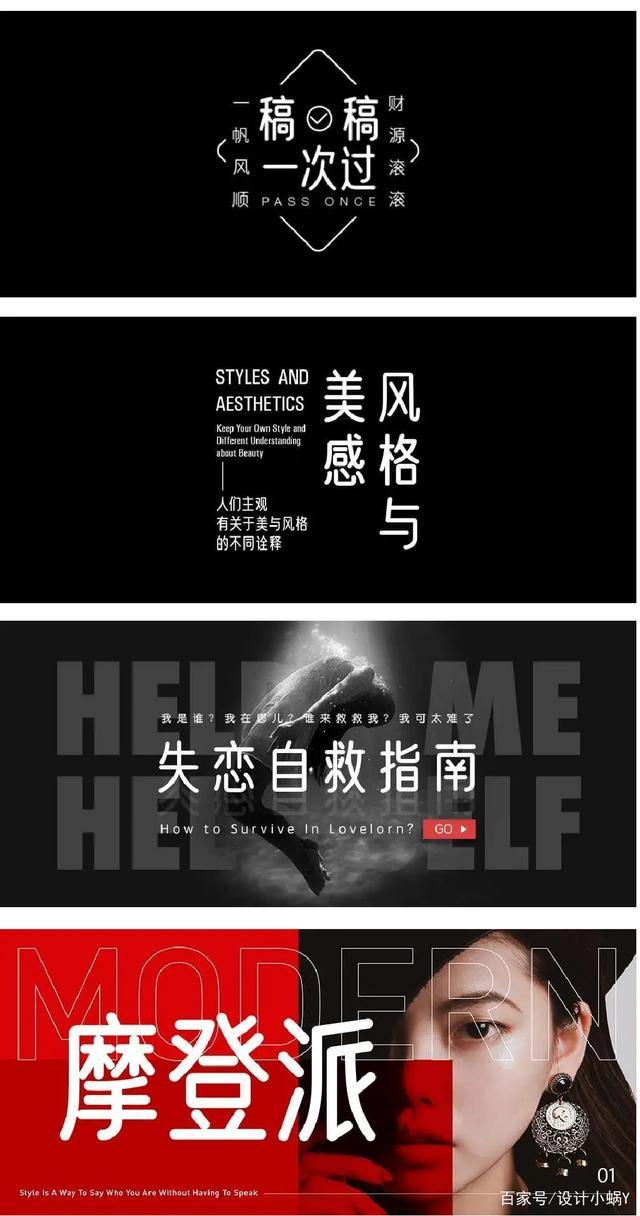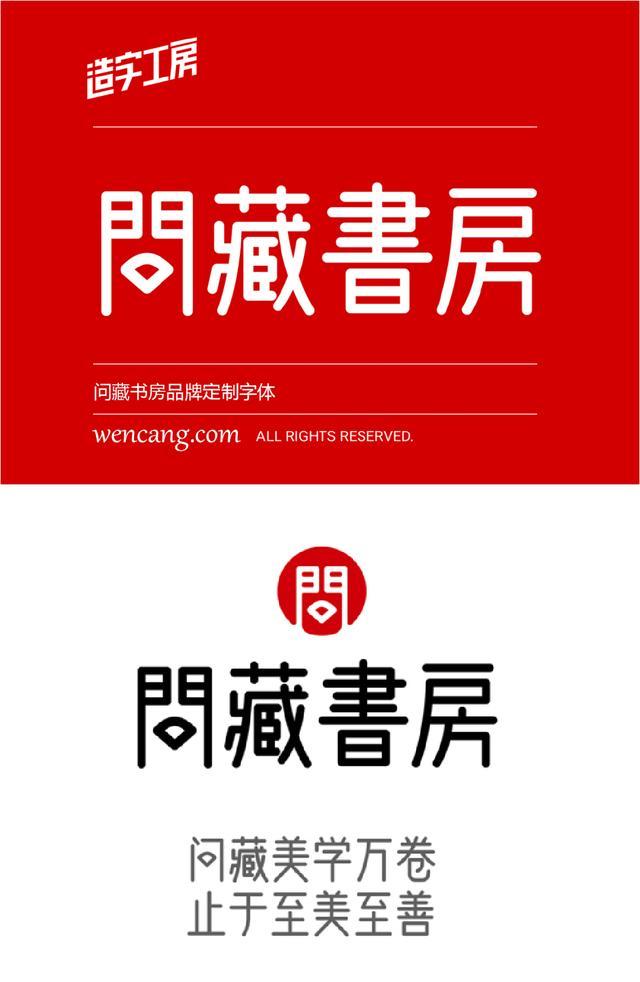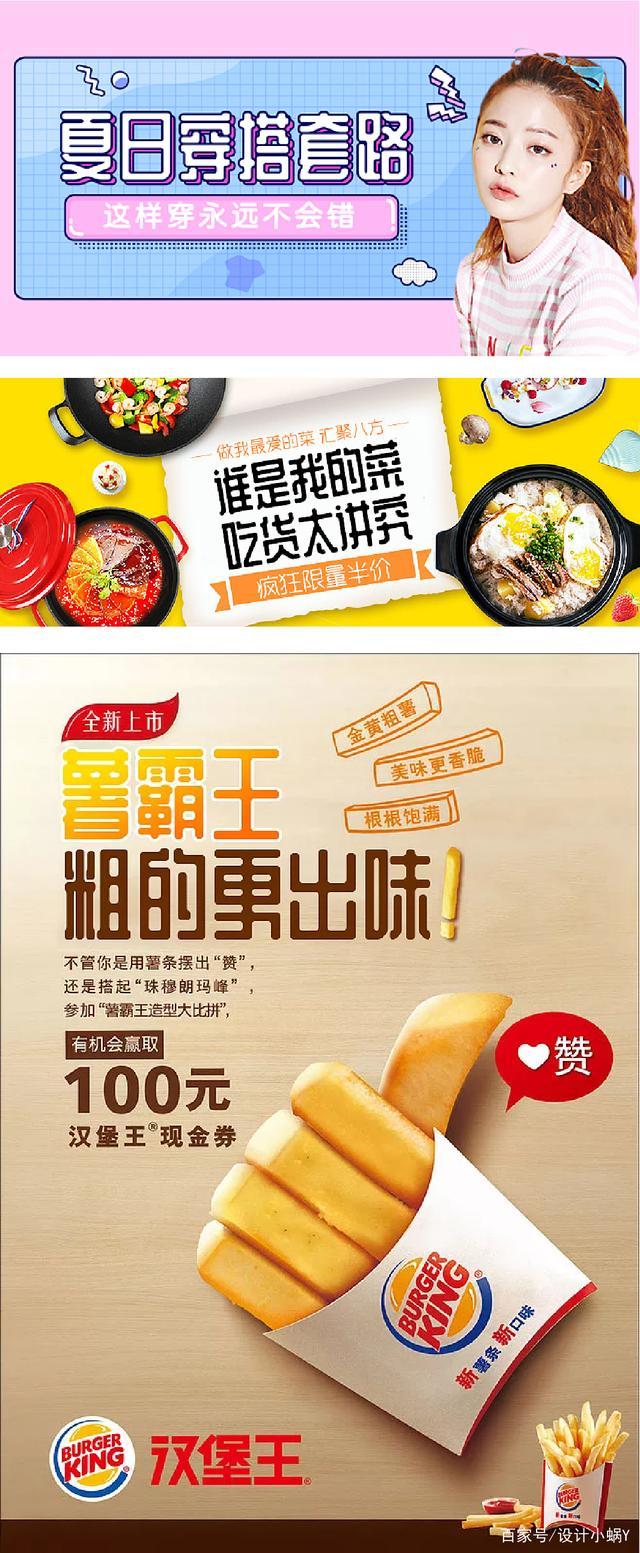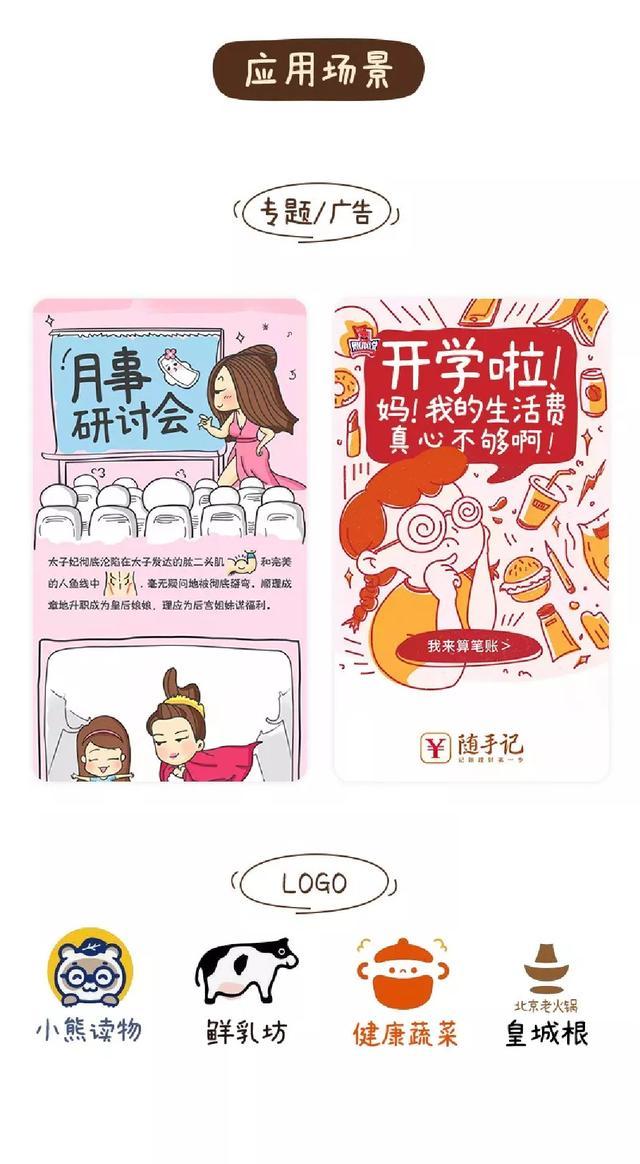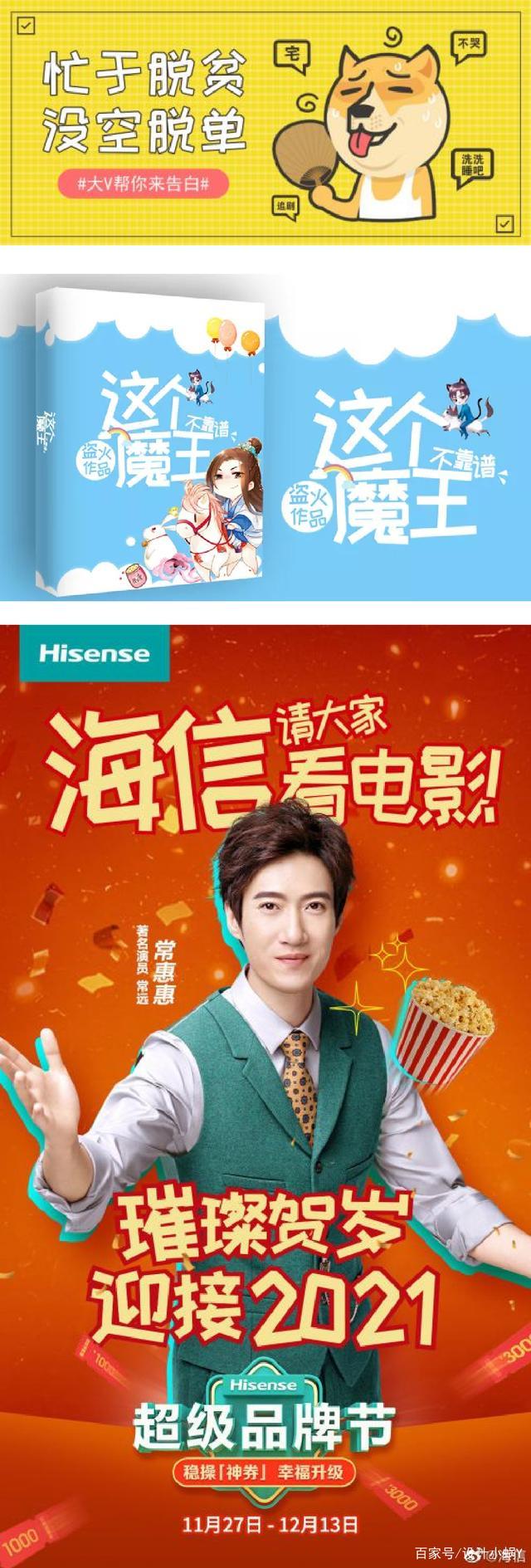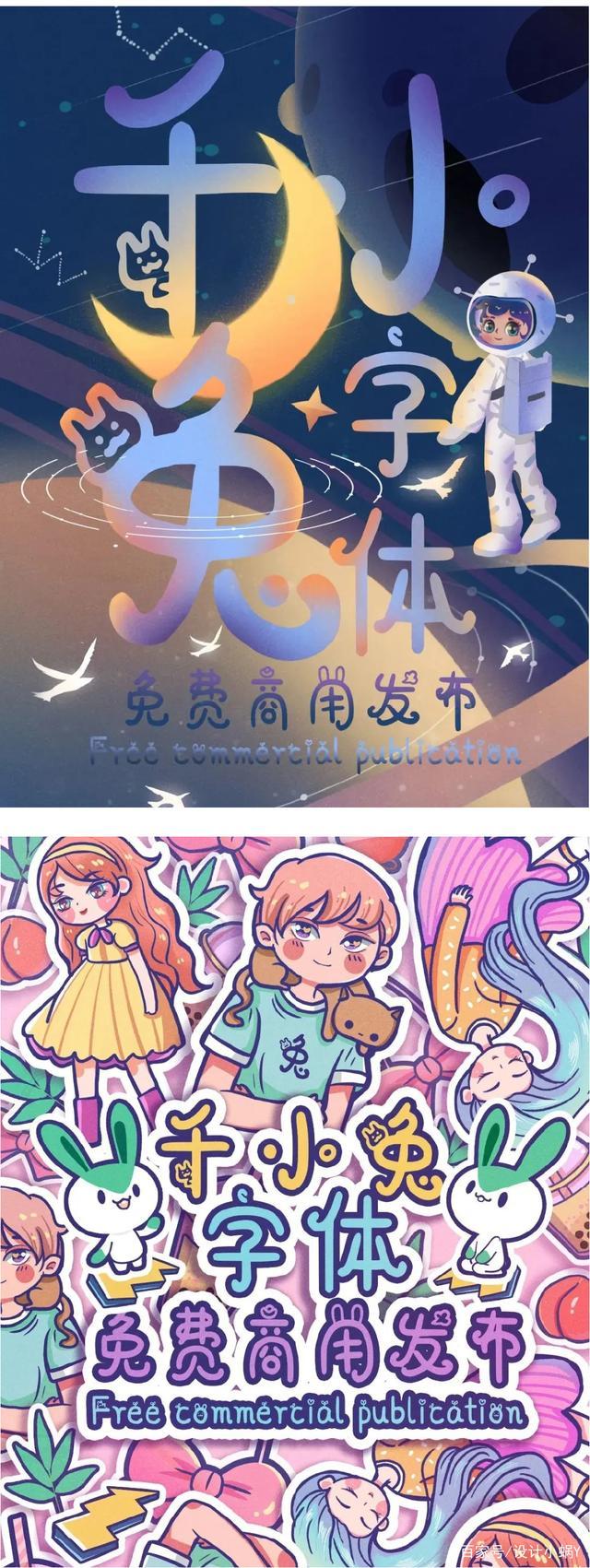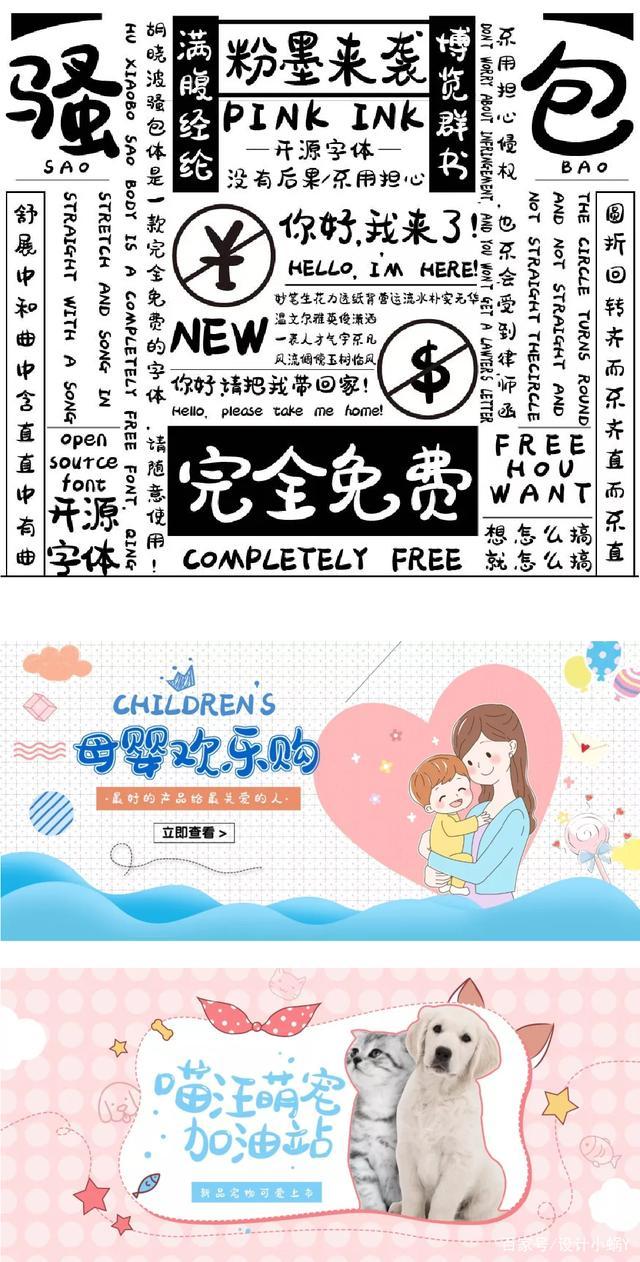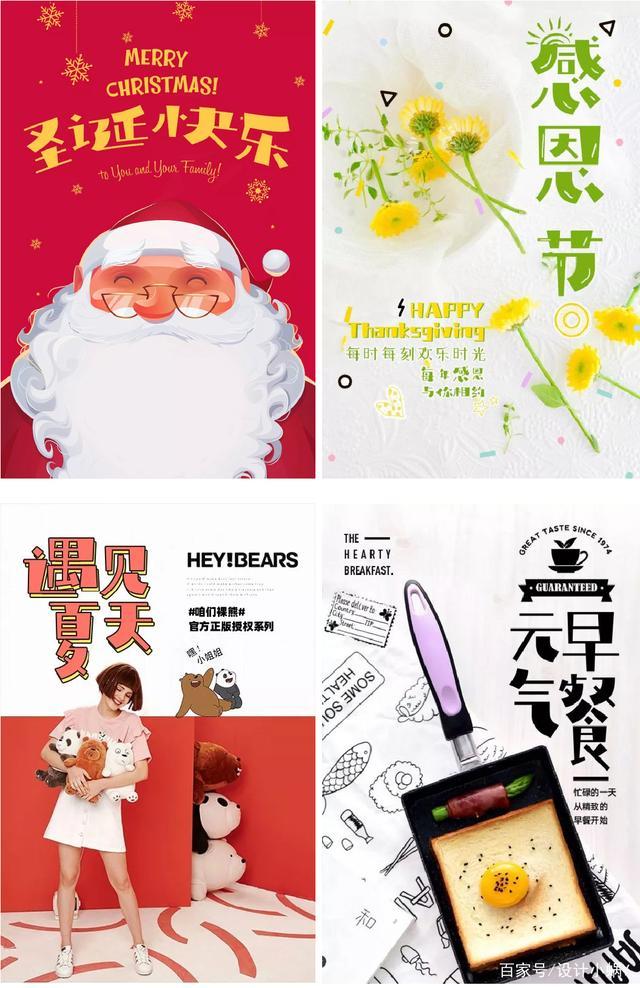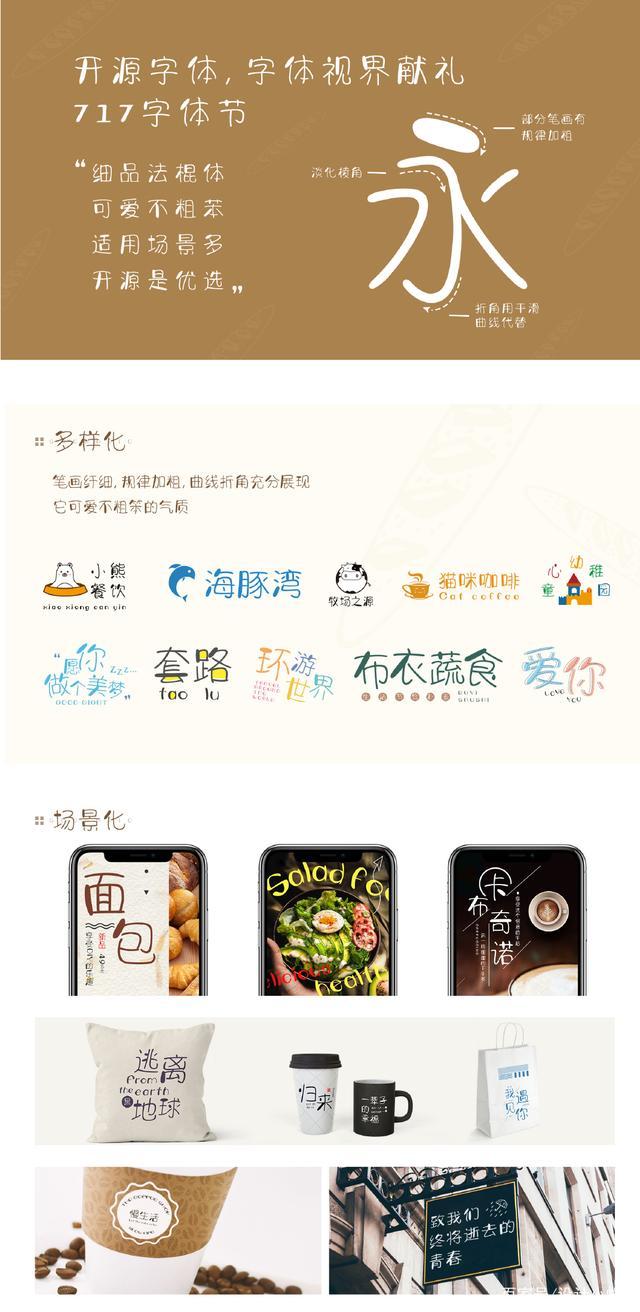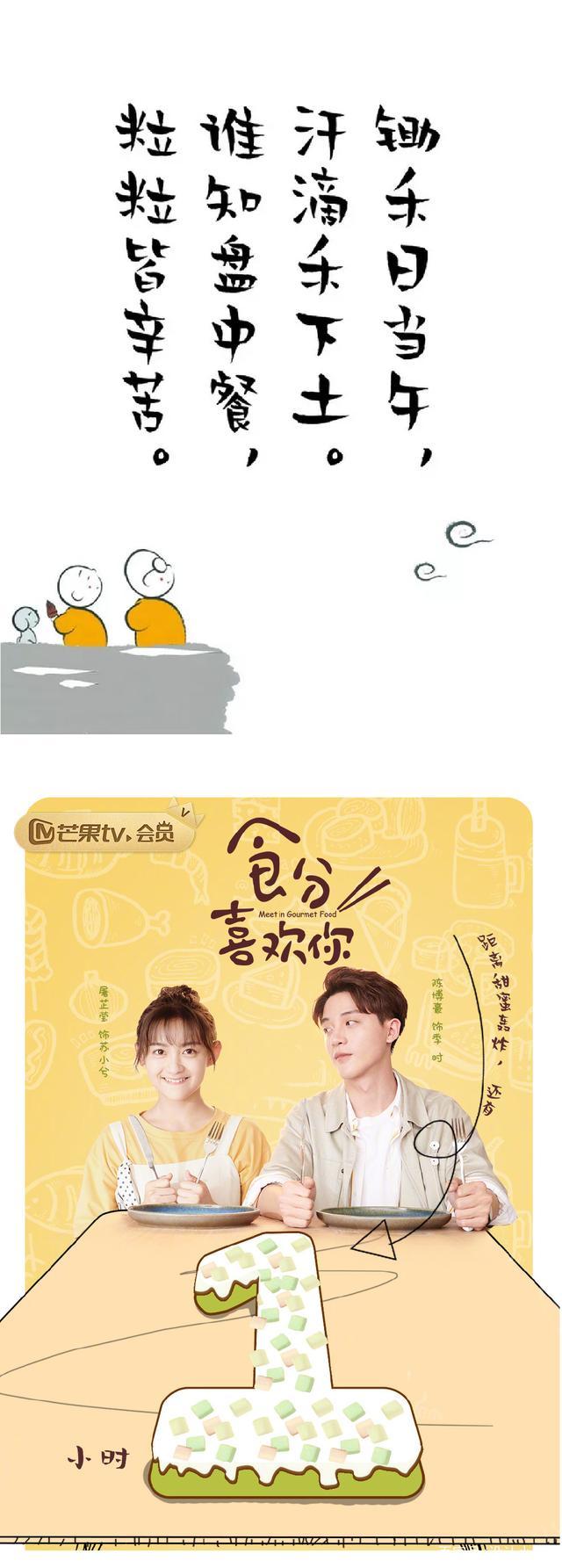
免费商用字体推荐—字体视界法棍体、包图小白体
江城圆体
最合适国内设计师运用的圆体字
“江城圆体”根据tw设计师规划的“源泉圆体”进行改造,把一些tw习气的字形进行简体化批改,更合适咱们大陆设计师运用,对简体中文的支撑也非常杰出,基本上不会存在缺字的问题,并且有6个字重,非常交心。
该字体将黑体中的衬脚悉数去除,内部角落也做得圆润滑润,削减字体中尖利的部分,也愈加契合全体圆润心爱的特色。
江城月湖体
圆润灵秀的歪斜圆体
江城月湖体根据江城圆体改造而成,将笔画横向拉宽,纵向压细,反正比照使得字体更具生机。
一起共同向右歪斜10度,圆润的笔画中又带着一点动感。
共具有3个字重。
优设好身体
具有亲和力和时尚感的圆润标题字体
优设好身体是一款亲和力、现代感极强的标题字体。
它以圆体字型为根底,经过瘦高的字面、倾向几许的曲线,让整宽字体赋有亲和力和时尚感。
问藏书房体
出现古拙美丽感的全新圆体
字体古拙美丽,中宫紧凑,视觉阅览极具层次感。
字字俊美且出现古雅之风,以精心规划赋予了汉字全新美感!
站酷庆科黄油体
字型立异、线条圆润的构思字体
该字笔划的每一个直角,都被处理成了半径为4pt的圆角,笔划视点尽量为笔直视点。
字体部首的右下角均为45°缺角,提高了字体视觉中心。
资料集市康康体
萌系心爱手写风格字体
「康康体」是一款萌系心爱手写风格中文字体,字库共2623 个汉字和字符,可以很好的满意日常规划运用。
站酷高兴体
轻松高兴风格的字体
整个字形向上歪斜,给人一种积极向上的感觉,并且横折和竖折的笔画都有弧线,没那么呆板,无论是笔画结构,仍是笔画粗细,都是灵敏的,是一例轻松高兴风格的字体。
包图小白体
镂空立体感的心爱字体
字形笔画去除了折笔的弧形,换之以平直的笔画,竖弯钩转为竖折,一起弱化了钩笔画,省去了许多笔画结尾的小尾巴,显得愈加直白心爱。
全体形状采用了镂空的制造技巧,增强了字体的立体感。
千图小兔体
生机诙谐的萌系构思字体
字体设计创意来源于千图网IP千小兔的形象,将心爱的千小兔融入字体设计中,尽显年青、生机与诙谐。
适用于各类心爱、少女风的海报和店招场景。
胡晓波骚包体
笔画随性自在的心爱字体
笔画随性自在和多变,采用了略带弧度的笔画,线条圆润,显得轻松惬意,天然舒展。
庞门正路轻松体
笔画粗细比照激烈,充溢童趣的字体
笔画粗细比照激烈,字形生动,以拙为巧,兴趣十足,充溢童趣,让人觉得轻松愉悦。
字体视界法棍体
憨态可掬,轻松惬意的心爱字体
在字形上淡化了棱角,笔画中心呈弧形外拓,将转弯的折角用滑润的曲线替代,部分笔画有规矩的加粗,再结合圆润滑润的笔画,显得心爱特性,憨态可掬,轻松惬意。
贤二体
诙谐诙谐的佛系字体
贤二体是汉仪字库联合北京龙泉寺动漫中心联合规划的一款佛系字体。
字体组合结构松懈,重心不稳,字形偏长,起笔收笔尖利且粗细比照显着,笔画蠢笨微带曲线感,具有诙谐诙谐的作用。
阿朱泡泡体
随意放松充溢卡通兴趣的字体
该字体去掉了一切尖利的折角,运用圆润的弧形替代,字体的巨细不完全共同让全体有了一种天然心爱的手拙感。
字体中的“口”字用不规矩的圆形替代,像极了小孩子顺手画的泡泡,让字体愈加心爱,童趣中不失生动。
仓耳舒圆体
笔形粗细过渡柔美的圆体
仓耳舒圆体的笔形一端较粗一端较细,天然过渡,圆润丰满,正经中带有几分慵懒,轻松愉悦,字形概括全体共同。
宗族字体包括5个字重。
仓耳非白
粗细比照显着风格激烈妥当的字体
仓耳非白是一款粗细比照显着、风格激烈、具有5个字重的宗族字体,结构方整,笔形简练、妥当,带有显着差异于其他字体的风格。
规划时,除了加粗笔形着重“黑”,也增加了部分细线着重“白”,字形转机处均做直角处理,撇捺相同以直线体现,终究成字出现激烈的粗细比照。
仓耳小丸子
天真烂漫狡猾心爱的字体
字形结构灵敏,选用粗细比照夸大的笔画,使字体更具视觉冲击力,搞怪的字型结构和出人意料的空间调整让字体多了几分狡猾心爱之气。
笔画错落有致,打破了许多固有的摆放形式,这款字在轻松的气氛中营造出天真烂漫的感触。